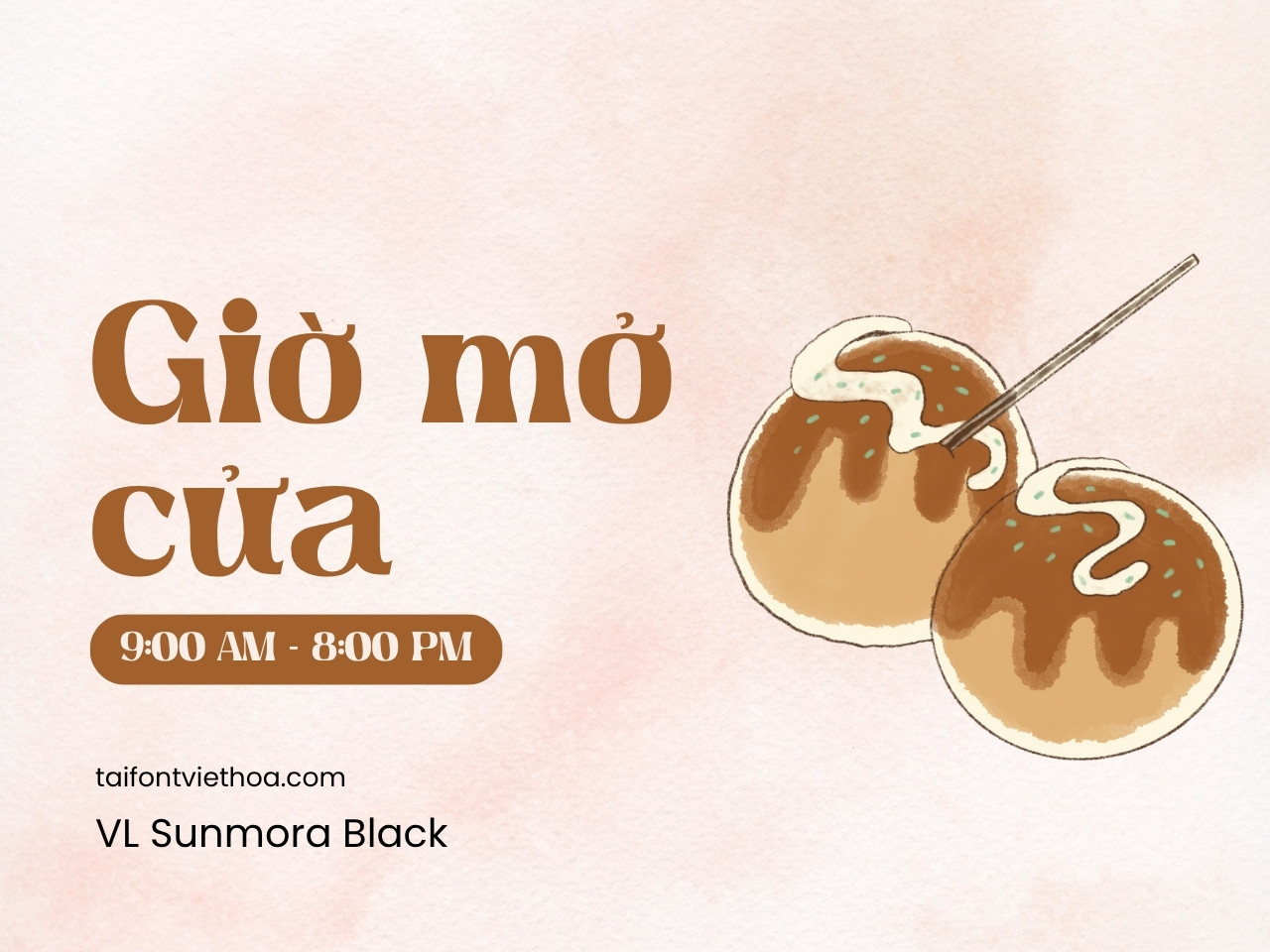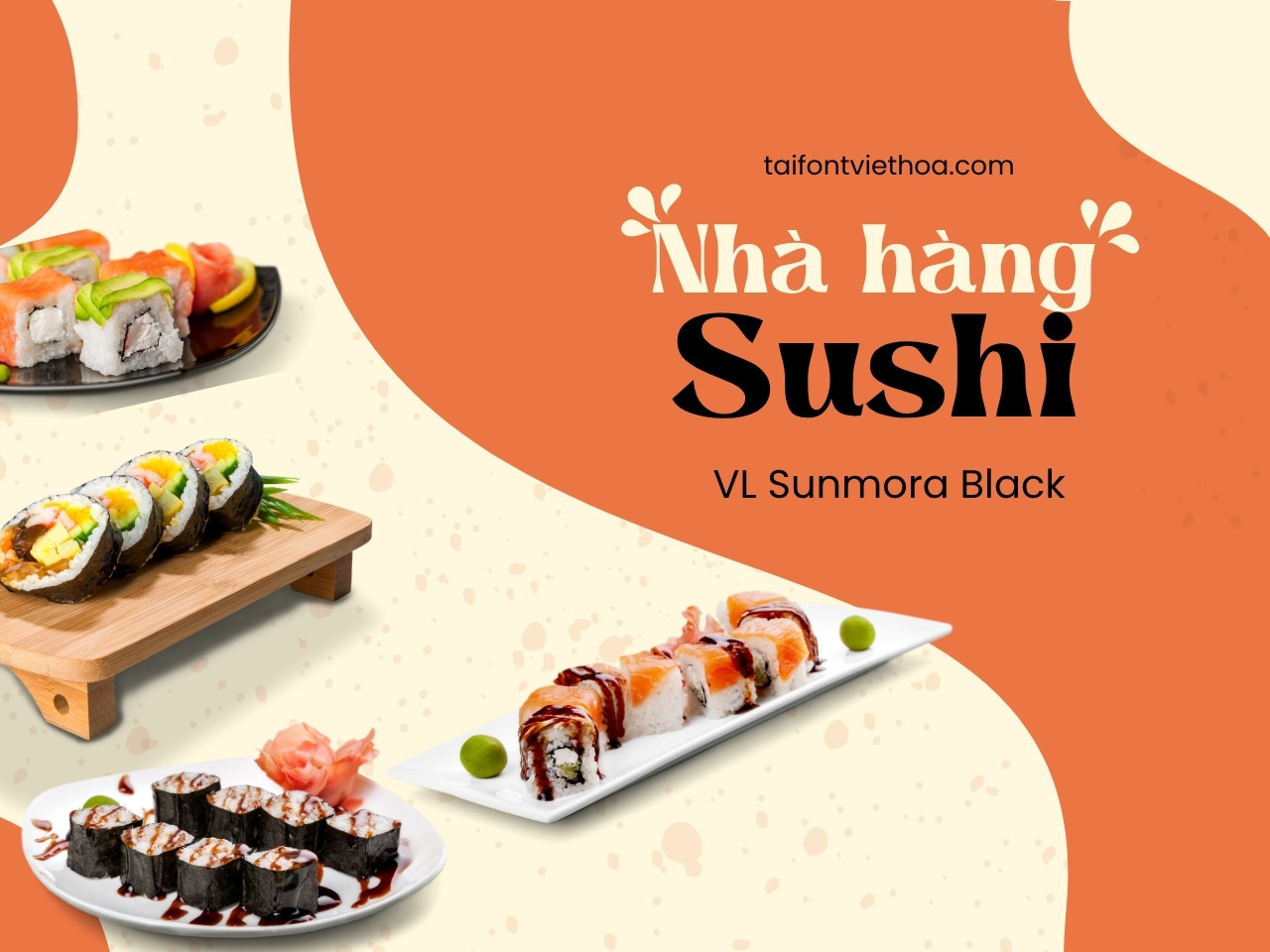
Font việt hóa VL Sunmora Black
Giới thiệu về font VL Sunmora Black
VL Sunmora Black là một kiểu chữ serif mang phong cách editorial sang trọng, đậm nét và thu hút, thường được ứng dụng trong các thiết kế mang tính nghệ thuật cao và định hướng thương hiệu cao cấp. Font được phát triển với độ tương phản mạnh mẽ giữa các nét dày – mảnh, kết hợp cùng các chi tiết cổ điển như đầu nét uốn cong tinh tế, tạo nên ấn tượng thị giác độc đáo. Phiên bản Việt hóa do Font Việt Linh thực hiện, hỗ trợ đầy đủ tiếng Việt với hệ dấu chuẩn xác, đảm bảo khả năng hiển thị mượt mà. Ngoài tiếng Việt, VL Sunmora Black còn hỗ trợ hơn 60 ngôn ngữ nhờ bộ mã Latin mở rộng. Font đã được taifontviethoa.com chọn lọc và ứng dụng trong các dự án thiết kế thương hiệu và truyền thông đòi hỏi sự đẳng cấp và chuyên nghiệp.
Đặc điểm thiết kế và ứng dụng của VL Sunmora Black
Font sở hữu thiết kế serif đậm, cấu trúc chữ mang hơi hướng biên tập cổ điển nhưng được cách tân phù hợp xu hướng hiện đại. Các ký tự lớn, mạnh, và sang trọng giúp font lý tưởng cho các thiết kế headline, tiêu đề in ấn, poster thời trang, hoặc bao bì mỹ phẩm cao cấp. Đặc biệt, font rất hiệu quả trong việc truyền tải thông điệp mang tính cao cấp và thẩm mỹ nghệ thuật.
VL Sunmora Black phù hợp với các dự án thiết kế như tạp chí thời trang, branding mỹ phẩm, bao bì sản phẩm sang trọng, bìa sách, danh thiếp, poster nghệ thuật và thiết kế website cao cấp. Ngành nghề lý tưởng: thời trang, mỹ phẩm, nội thất cao cấp, xuất bản, truyền thông và bất động sản hạng sang.